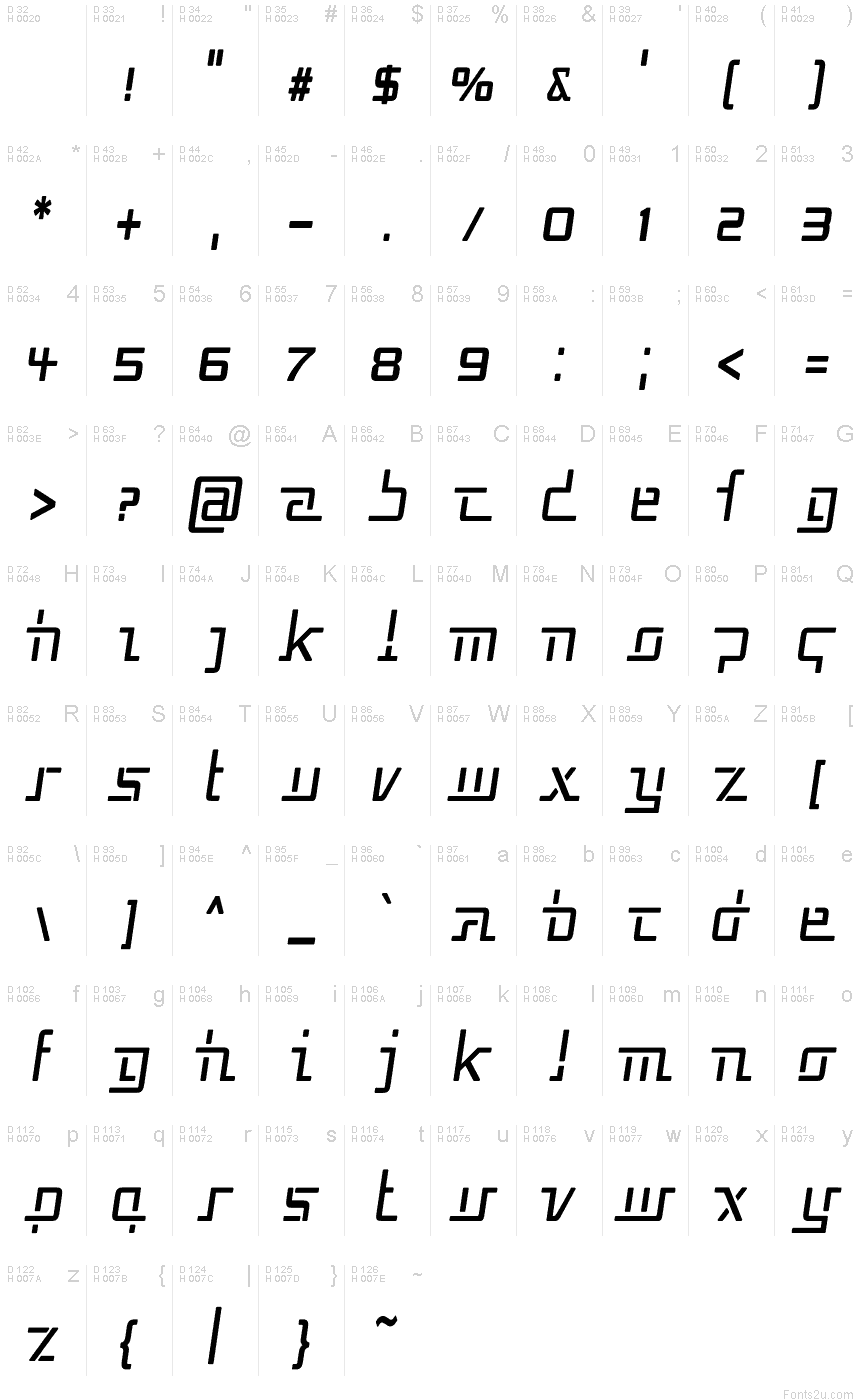
Republika V Cnd Italic
Republika V Cnd Italic od Apostrophe to darmowy, futurystyczny krój pisma typu display o szybkim, niemal torowym rytmie. Litery pochylają się do przodu w długich, niskich pociągnięciach, łącząc kanciaste krzywizny ze ściętymi rogami, dzięki czemu cały alfabet przypomina bardziej ciągły sygnał niż zbiór oddzielnych znaków.
To naturalny wybór dla brandingu technologicznego, ulotek klubowych, ekranów tytułowych gier, okładek sci-fi czy plansz tytułowych w animacjach, gdzie darmowy font musi sugerować szybkość i technologiczny charakter, nie stając się przy tym tylko ciekawostką. Świetnie sprawdza się również w krótkich nagłówkach i logotypach, ponieważ połączone, przypominające tory litery nadają nawet krótkim słowom elegancki, kierunkowy impet.